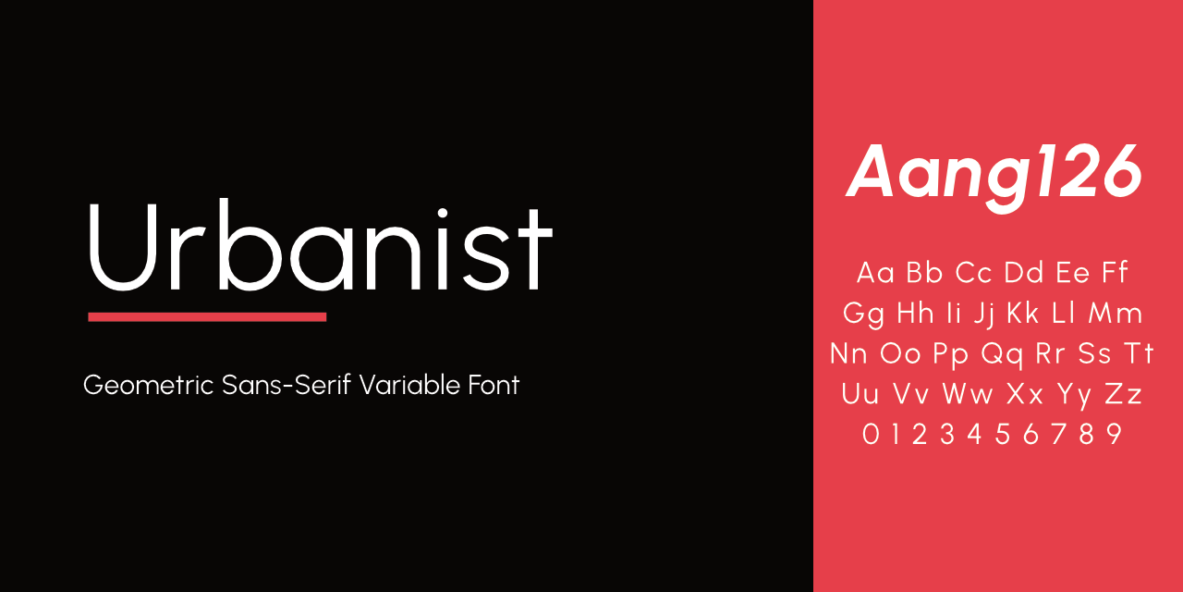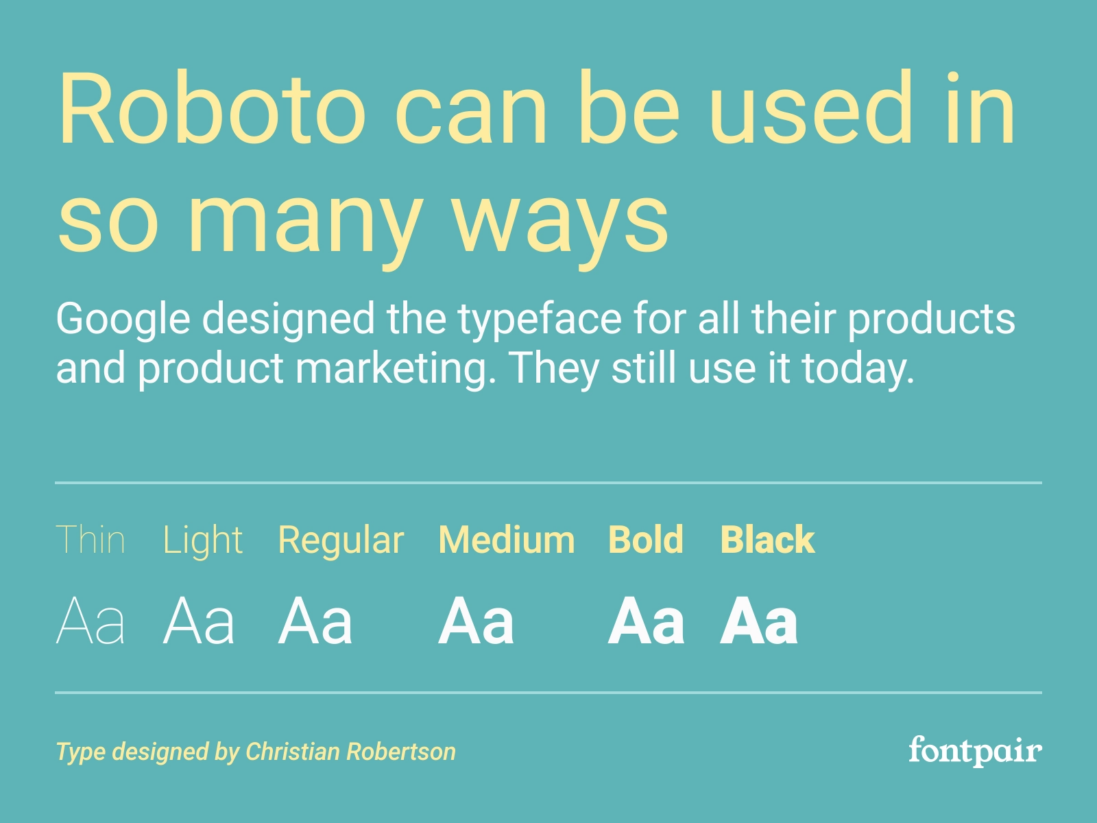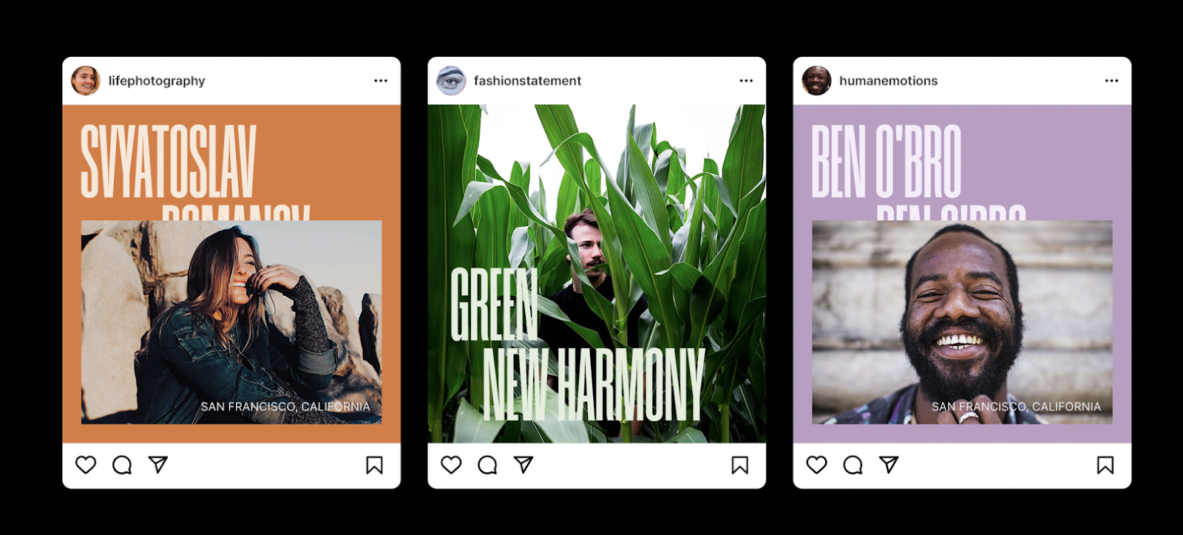
14 font chữ thiết kế đáp ứng mọi “jobs” của Designer (Phần 2)
Tiếp nối phần 1, danh sách sau đây sẽ đưa bạn đến với vùng đất đa dạng của Typeface Design, nơi tập hợp các kiểu font chữ thiết kếthuộc mọi phong cách, từ đơn giản, phóng khoáng đến hình học, phức tạp hay thậm chí ẩn chứa những giá trị về lịch sử và nhân sinh.
Với 7 cái tên đầu tiên, chúng ta được chứng kiến sự ra đời của những kiểu chữ mới mẻ, độc đáo, tập trung thể hiện các yếu tố cơ bản của Typeface Design như độ dày mỏng, cao thấp, tương phản, hình khối, v.v… Ở phần 2 cùng 7 font chữ thiết kế còn lại, bài viết giúp bạn khám phá thế giới phức tạp của nghệ thuật thiết kế con chữ, không chỉ là quy tắc hay cấu trúc mà còn chứa đựng thế giới quan về con người, cuộc sống hay câu chuyện và phong cách riêng biệt mà nhà thiết kế luôn theo đuổi xuyên suốt hành trình sáng tạo.
8. Font chữ thiết kế Urbanist của Corey Hu
Font chữ thiết kế Urbanist thuộc kiểu chữ sans-serif hình học, sở hữu độ tương phản thấp và được lấy cảm hứng từ những thiết kế hiện đại. Kiểu chữ này ra đời vào năm 2020 và là thành quả sáng tạo của Cory Hu – nhà thiết kế kiểu chữ tại Hoa Kỳ. Được xây dựng từ các hình dạng cơ bản, trạng thái trung lập của Urbanist giúp kiểu chữ trở thành lựa chọn hiển thị hàng đầu cho các sản phẩm in ấn hoặc thiết kế ở định dạng kỹ thuật số. Urbanist hiện có sẵn dưới dạng một phông chữ biến đổi, với các trục điều chỉnh độ đậm (từ 100 – 900) và độ nghiêng (từ 0 – 1).
9. Font chữ thiết kế Humane của Rajesh Rajput
Humane là font chữ thiết kế miễn phí rất xứng đáng để bạn tải xuống. Thuộc kiểu chữ sans-serif với font-style vô cùng hẹp, Humane hỗ trợ đa ngôn ngữ cùng hệ thống màu sắc ấm áp, thân thiện. Kiểu chữ được tạo ra bởi Rajesh Rajput, nhà thiết kế chuyên về Typeface đến từ Ấn Độ. Humane hiện sở hữu 7 cấp độ dày, từ mỏng đến đến đậm (thin – bold), phù hợp ứng dụng trong việc hiển thị các dòng headline, tiêu đề, logo, v.v… “Kiểu chữ này dành cho tất cả mọi người.” – Rajesh bổ sung thêm: “Cuộc sống không công bằng với bất kỳ ai, và mọi người đều phải đối diện với những câu chuyện của riêng mình. Tuy nhiên, tình yêu và lòng trắc ẩn vẫn luôn tồn tại. Hãy kiên trì và tận hưởng bất cứ điều gì mà bạn sở hữu.”
10. Roboto của Christian Robertson
Roboto là kiểu chữ sans-serif do Christian Robertson thiết kế dành cho hệ điều hành Android vào năm 2011. Cùng năm, Google Fonts đã tích hợp font chữ thiết kế này nhằm giúp cho giao diện web và thiết bị di động trở nên hiện đại, rõ ràng hơn. Christian hiện đang làm việc tại Google và studio thiết kế kiểu chữ của riêng mình – Betatype.
Nổi bật với thiết kế hình học mang cảm giác nhân văn, được sử dụng rộng rãi trên nhiều nền tảng và thiết bị khác nhau, từ trang web đến ứng dụng di động. Ngày nay, font chữ thiết kế Roboto đã trở thành một trong những font chữ phổ biến nhất trên Google Fonts. “Roboto mang bản chất kép”, Christian giải thích “Nó sở hữu phần lớn cấu trúc ở dạng hình học. Đồng thời, vẫn chứa đựng những đường cong thân thiện và cởi mở. Trong khi một số người cố gắng tạo ra nhịp điệu cứng nhắc cho thiết kế kiểu chữ của họ, Roboto không thỏa hiệp với điều này, chúng tôi cho phép các chữ cái được sắp xếp với chiều rộng tự nhiên của riêng nó.”